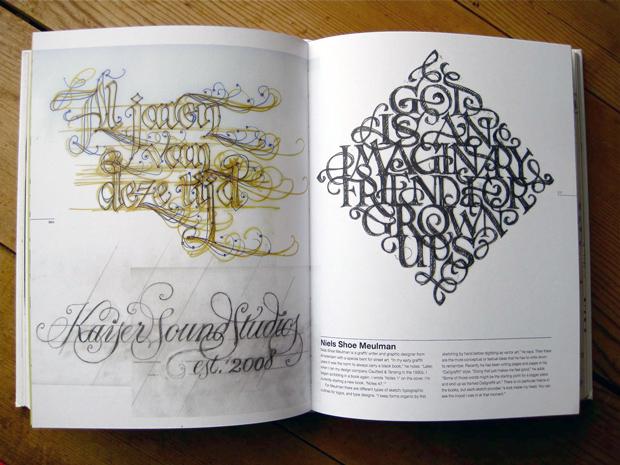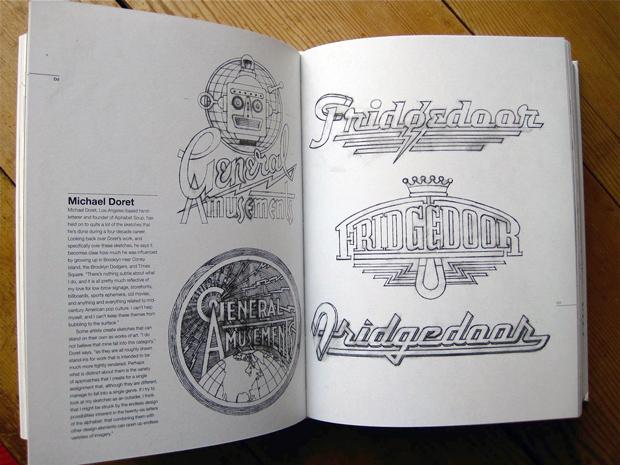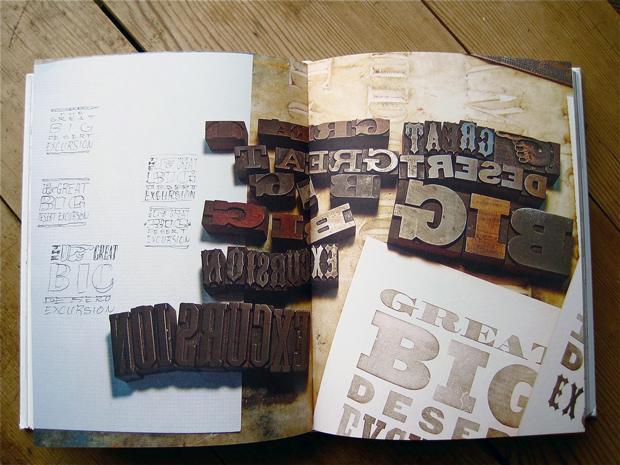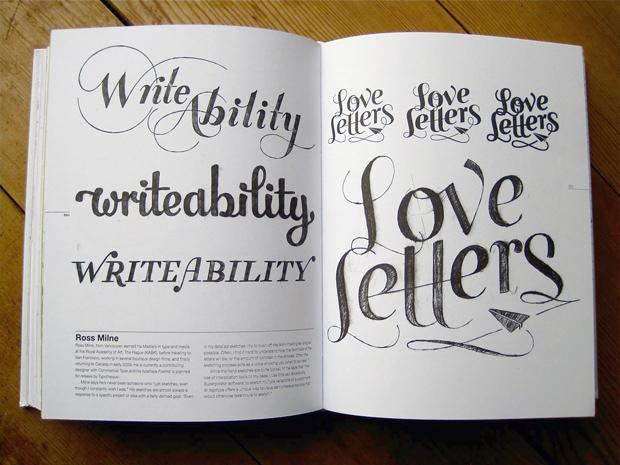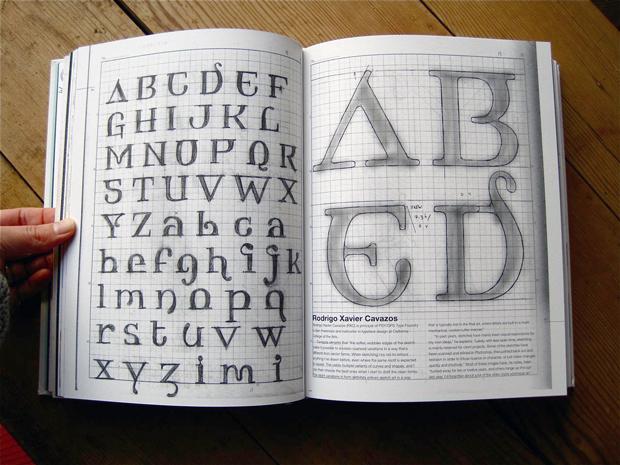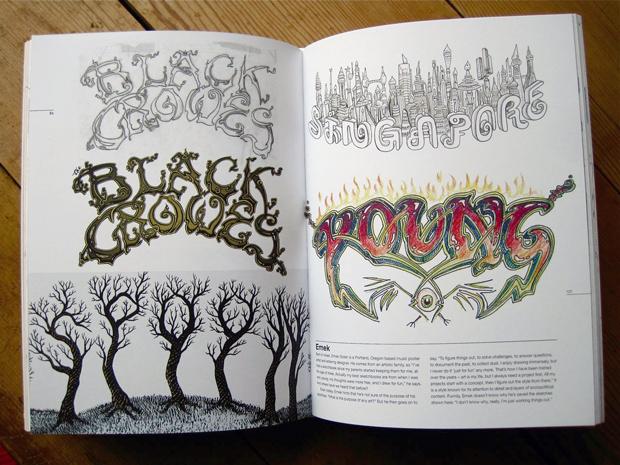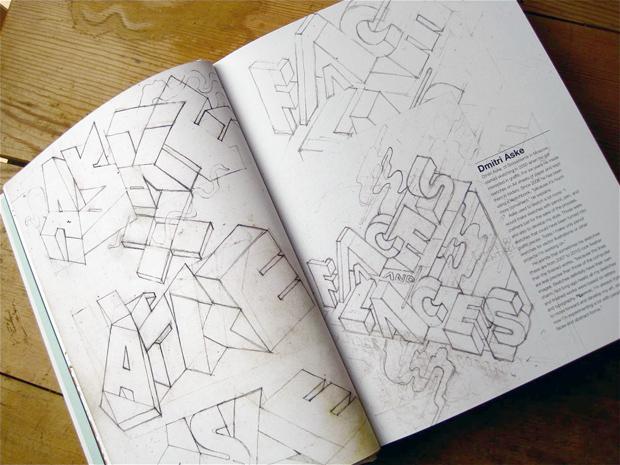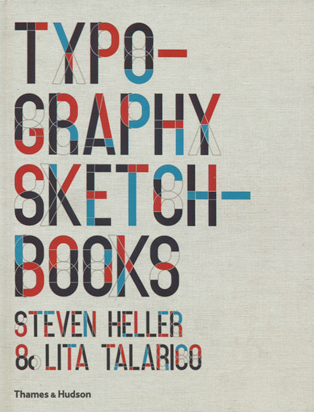
Typography Sketchbooks
Den beiden Autoren Steven Heller und Lita Talarico ist eine bemerkenswerte und umfangreiche Sammlung gelungen: Ihr Buch Typography Sketchbooks bietet spannende Einblicke in typografische Skizzenbücher aus aller Welt. Weit über 100 renommierte Designer und Typografen (zum Beispiel Erik Spiekermann) haben sich bereitwillig über die Schulter blicken lassen und ihre Skizzen für die Veröffentlichung in diesem Buch freigegeben. Dies scheint umso bemerkenswerter, wenn man weiß, wie sorgfältig verborgen die Skizzenbücher der meisten Gestalter normalerweise ein eher schattiges Schubladendasein fristen. Die interessierte Öffentlichkeit bekommt ja in der Regel bestenfalls die veröffentlichten, fein ausgearbeiteten Resultate all jener Gestaltungsprozesse zu sehen, an deren Anfang einmal ein paar kühne Striche in einem Skizzenbuch standen. Doch gerade diese ersten Skizzen, angefertigt, um spontane Ideen auf die Schnelle an der Flucht zu hindern, haben oft ihren ganz besonderen Reiz. Geschwind aufs Blatt geworfen oder auch liebevoll ausgearbeitet verraten sie eine Menge über den Kreativprozess, der – normalerweise unsichtbar – im Gestalterkopf abläuft. Die gezeigten Beispiele reichen von groben Skizzen über fein gezeichnete Ausarbeitungen bis hin zu kompletten Illustrationen – die Grenzen zwischen den Disziplinen verlaufen fließend. Und auch die Palette der Ausdrucksmittel ist breit gefächert: von Bleistift, Filzstift, Feder und Pinsel bis hin zu Vektorgrafiken ist alles vertreten.
Neben dem inhaltlichen Gewicht bringt das Buch mit seinen 368 Seiten beachtliche anderthalb Kilo auf die Waage und eignet sich damit nicht gerade als Lektüre für unterwegs – aber das soll es ja auch nicht sein. Der sorgfältig aufbereiteten Darstellung der Skizzenbücher wird in diesem Buch fast die komplette Fläche zur Verfügung gestellt, Einleitung und Kommentierung durch die Autoren beschränken sich auf das Notwendige. Hübsches Detail sind die Seitenzahlen, die sich mit zunehmendem Wert an den rechten Blattkanten des Buches nach oben bewegen. Als einziger Kritikpunkt zu nennen wäre vielleicht die Leserlichkeit, die durch die Entscheidung, die Einleitung in mattem Blau auf dunkelgrauem Hintergrund zu drucken, sowie die erläuternden Texte zu den Designern auf transparenter Fläche über deren Skizzen zu setzen, in einigen Fällen ziemlich erschwert wird.
Steven Heller hat mehr als 130 Bücher zum Designthemen geschrieben oder herausgegeben. 33 Jahre lang war er Art Director bei der New York Times und dem U&lc-Magazin und macht sich in zahlreichen Projekten um die Förderung des kreativen Nachwuchses verdient.
Lita Talarico ist Mitbegründerin des »School of Visual Arts MFA Design Program« in New York City und verschiedener weiterer Designprojekte, unter anderem in Italien. Sie hält Lesungen zu Designthemen auf der ganzen Welt und engagiert sich zusammen mit Steven Heller für die Förderung des kreativen Nachwuchses.
Mein persönliches Fazit: Ich gebe es zu: Ich habe ein Faible für Skizzenbücher. Und zwar sowohl für eigene, die ich in zahlreichen Varianten besitze und in unregelmäßiger Reihenfolge mit Zeichnungen fülle als auch für die Skizzenbücher von befreundeten Künstlern und Kollegen, in die ich ab und zu mal einen Blick werfen darf. Skizzenbücher bewahren zwischen ihren Deckeln eine Fülle flüchtiger Gestaltergedanken vor dem Vergessen und dessen profanem Verbündeten, dem Papierkorb. Für mich, die ich aus dem illustrativen Bereich komme, ist Typography Sketchbooks eine schöne Inspirationsquelle, ein informatives Bilderbuch sozusagen. Ich erfreue mich am lebendigen Duktus und der zeichnerischen Qualität sehr vieler der gezeigten Beispiele und an den Ideen, die in den Skizzen sichtbar werden.